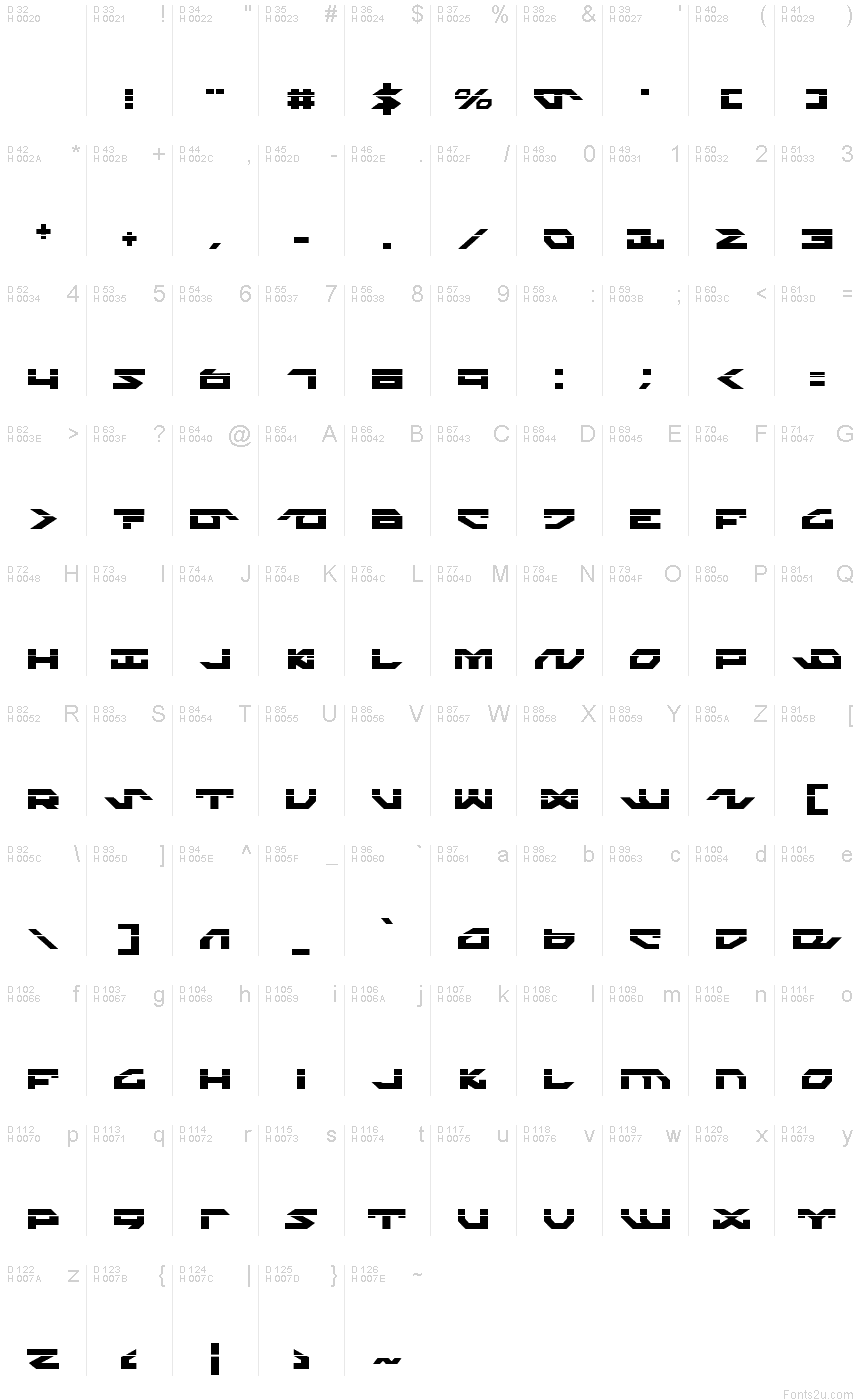
Nightrunner Laser, di Iconian Fonts, è un carattere tipografico futurista gratuito in stile stencil, definito da tagli netti e ampie forme geometriche. Tratti spezzati e tagli diagonali conferiscono alle lettere un ritmo rapido e meccanico, caratterizzato da una spiccata atmosfera fantascientifica.
La sua costruzione frammentata crea un effetto dinamico e ad alta energia nei titoli di film sci-fi e nel branding di videogiochi, mentre la grafica per gli e-sport e i poster di eventi acquistano un taglio digitale deciso. Usa questo carattere gratuito su copertine di album o packaging tecnologico quando il design richiede lettere dall'aspetto ingegneristico, aggressivo e strettamente legato all'immaginario futuristico.